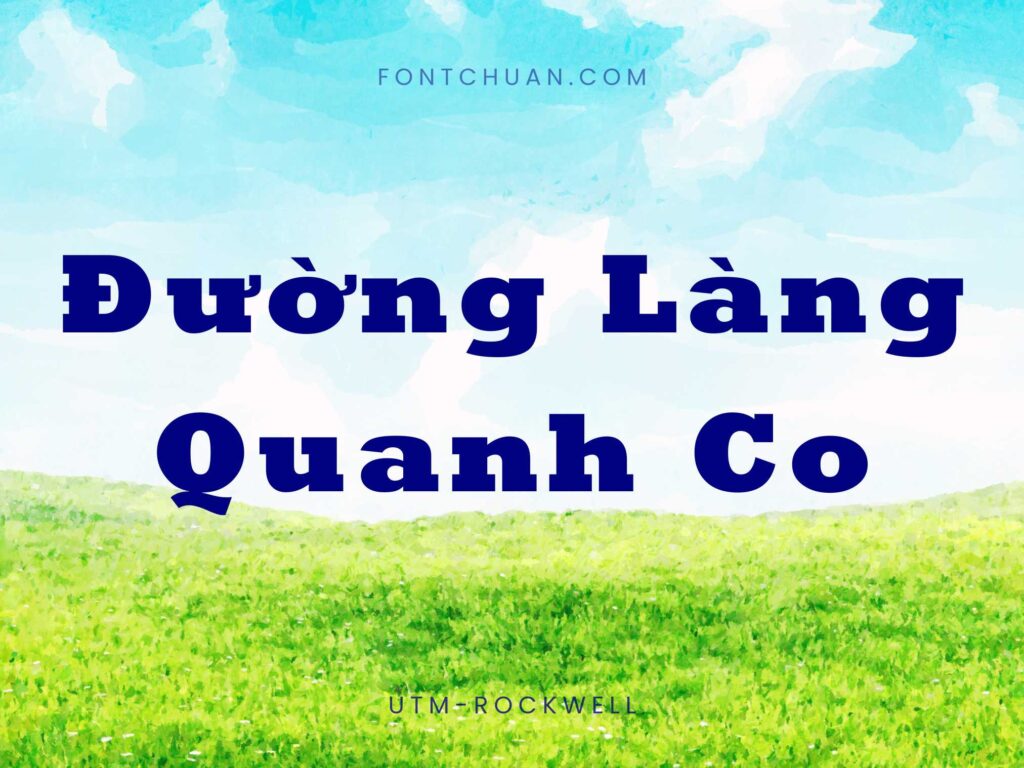
Font UTM Rockwell Việt Hóa
UTM Rockwell là một Font Slab Serif mang phong cách cổ điển và mạnh mẽ, được thiết kế với các đường nét rõ ràng và chắc chắn, tạo cảm giác vững chãi và đáng tin cậy trong các thiết kế. Font này nổi bật với nét chữ đậm, cân đối và dễ đọc, phù hợp với nhiều mục đích sử dụng từ in ấn đến thiết kế thương hiệu. Font đã được Việt hóa để hỗ trợ tiếng Việt, giúp mở rộng khả năng ứng dụng. Thành viên của Font Chuẩn đã sưu tầm và giới thiệu font này nhằm đáp ứng nhu cầu bạn đọc, cung cấp nguồn tham khảo chất lượng và ứng dụng thực tế vào các dự án thiết kế
Về đặc điểm thiết kế, UTM Rockwell có kiểu dáng serif với độ dày đồng đều, đường nét vững chắc và phong cách cổ điển. Font này phù hợp với nhiều ứng dụng như thiết kế logo, tiêu đề, poster, bao bì sản phẩm và nội dung thương hiệu. Các ngành nghề như quảng cáo, giáo dục, công nghệ và thiệp cưới có thể tận dụng font này để tạo nên sự sang trọng và chuyên nghiệp trong các sản phẩm thiết kế
Tác giả: Drawperfect
Việt hóa: Zenis